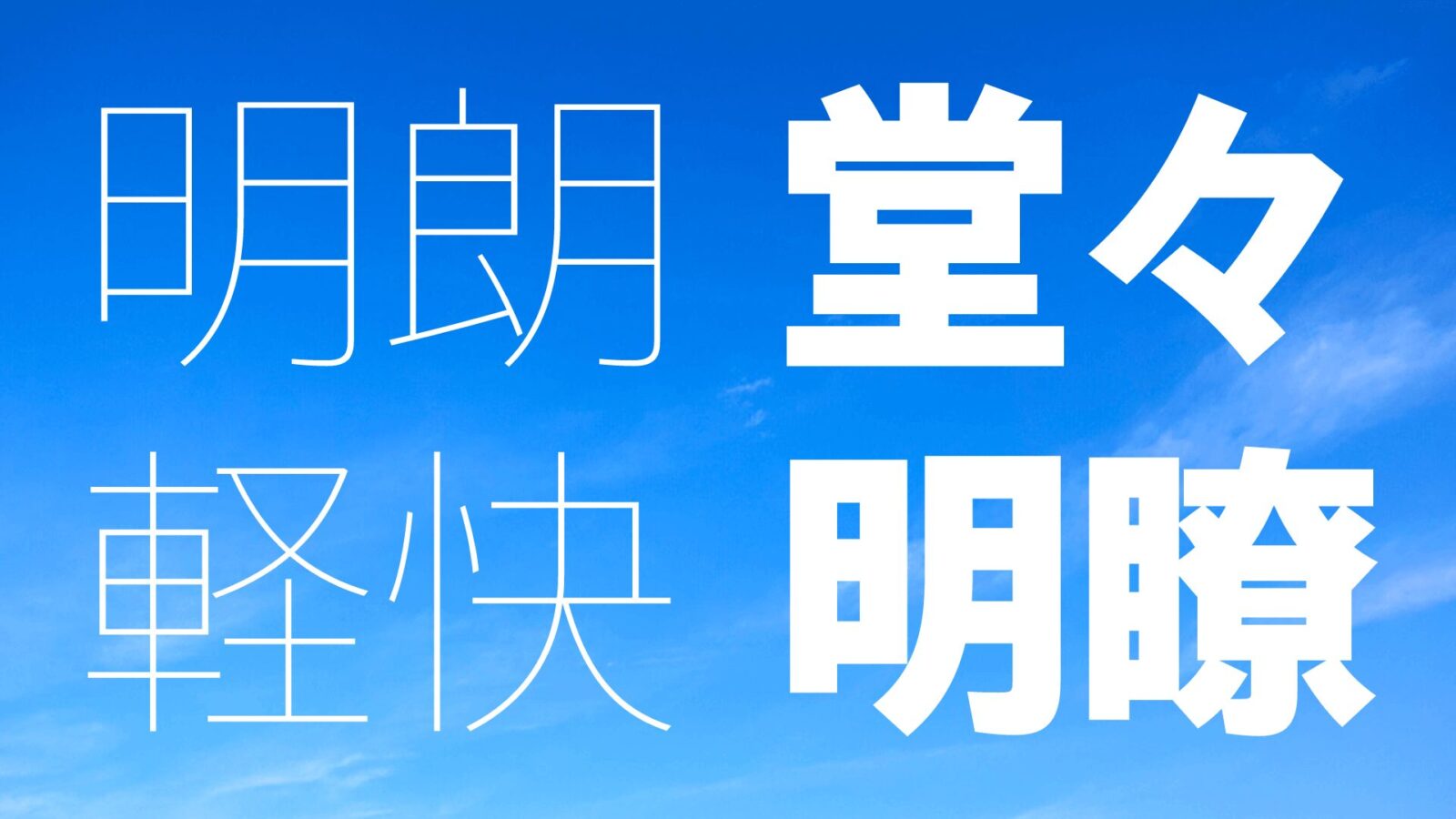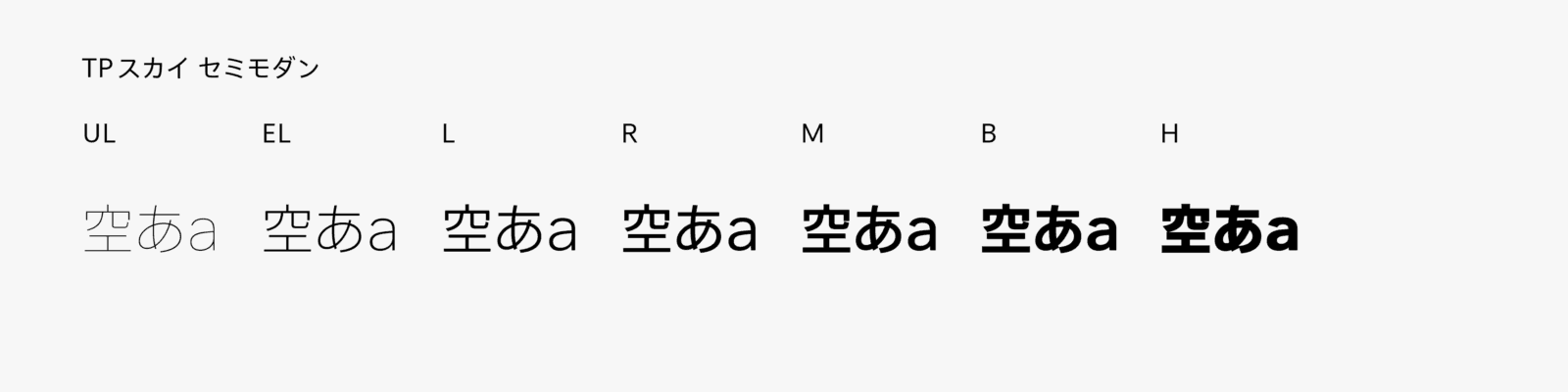
タイププロジェクト、ゆったりとしたフトコロで安定感のある「TPスカイ セミモダン」を発表
幅広いシーンで使える、フラットで明るい印象のサンセリフ書体
TPスカイ ファミリーは、ウエイト・コントラスト・字幅・フトコロ(字画内の内部空間)の4つの軸を持つ初めての日本語フォントです。TPスカイ セミモダンのフトコロは、中庸なTPスカイと極めて広いTPスカイ モダンの中間に設定しています。ほどよいフトコロの広さと、TPスカイ ファミリーに共通するシンプルを突き詰めたデザインを合わせ持つゆるやかで安定感のある書体です。
TPスカイ セミモダンは、TPスカイ モダンと同様に、全角文字の正方形の空間を活かすデザインにより、文字詰めを行うことなくベタ組みで整然とフラットな組版を実現します。ゆったりとしたフトコロは、小さいスぺースで文字を大きく扱いたいときに効果を発揮し、簡素なデザインのストロークにより文字が潰れにくく高い視認性を保ちます。
欧文は、非常にシンプルなサンセリフ体としてオーソドックスなデザインです。大きな文字にするために、x-height(エックスハイト)をやや高めに設定し、和欧の字粒を揃えるため和文に対して欧文のベースラインを少し低く目に設定しています。
タイププロジェクトの代表取締役 鈴木 功は、「TPスカイ ファミリーは、その名が示すとおり青空のように澄み切ったデザインが持ち味で、広大なデザイン空間を澄んだ空気で満たすことができるような書体を目指しました。なかでもこのTPスカイ セミモダンは、とりわけ明るさと親しみにあふれる書体です。小さいサイズでの視認性も高く、TPスカイ ファミリーがさらに幅広いシーンで活用されることを期待しています」と述べています。
TPスカイ セミモダンは、UL(ウルトラライト)、EL(エクストラライト)、L(ライト)、R(レギュラー)、M(ミディアム)、B(ボールド)、H(ヘヴィ)の全7ウエイトです。
これにより、TPスカイ ファミリーは、TPスカイ セミモダン 7ウエイト、TPスカイ モダン 8ウエイト、TPスカイ 48フォント(ウエイト×コントラスト×字幅)、TPスカイ クラシック(ウエイト×コントラスト)16フォント、TPスカイ セミクラシック(ウエイト×コントラスト)16フォントの全95フォントになりました。